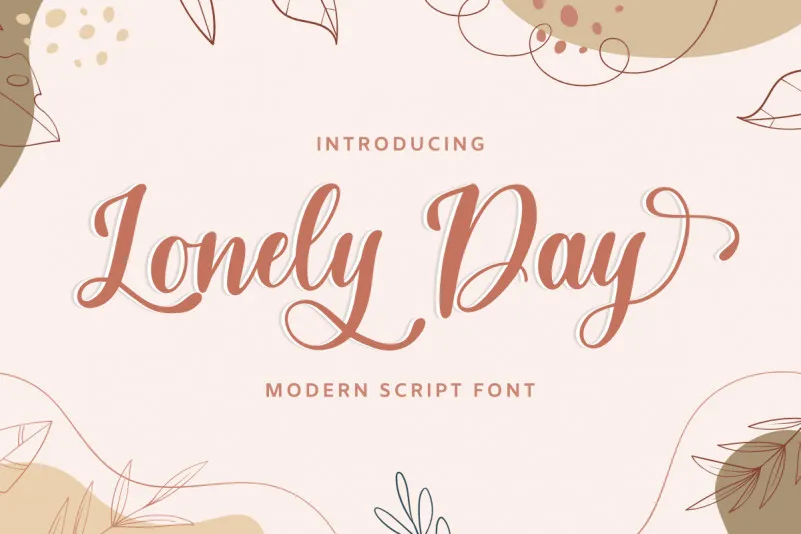
A ‘Lonely Day Font’ é uma delicada fuçula cheia de detalhes, perfeita para adicionar charme aos projetos digitais e impressos. Suas características incluem ligaturas adicionais e alternativas estilísticas que dão um toque sofisticado às letras. Este font foi criado com um tema divertido, tornando-o ideal para uma ampla variedade de usos, desde selos e cartões de visita até assinaturas e materiais promocionais. Com sua elegância discreta e personalidade encantadora, a ‘Lonely Day Font’ é certamente uma opção inovadora que encaixa-se perfeitamente em seu portfólio de design. Seja você criando um selo para eventos ou uma camisa de têxtil para casamentos, esta fuçula trará brilho ao seu trabalho.
Designer: jimtypestudio